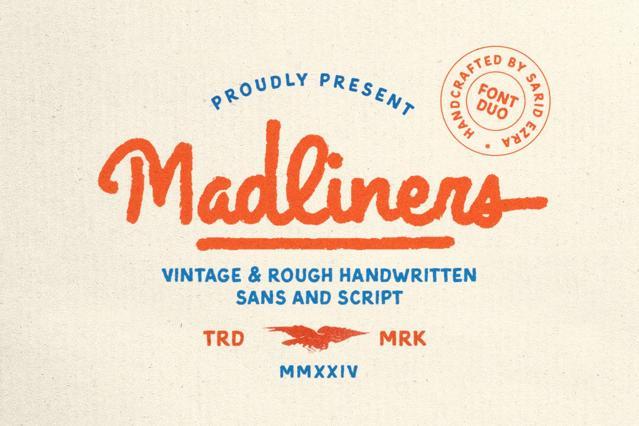
Познакомьтесь с Madliners — крепким, ручной работой созданным шрифтом, который сочетает в себе винтажное письмо и необузданный стиль. Это шедевр для тех, кто хочет сделать свой проект уникальным!
🖋️ Откройте для себя Madliners — неординарный шрифт дуо!